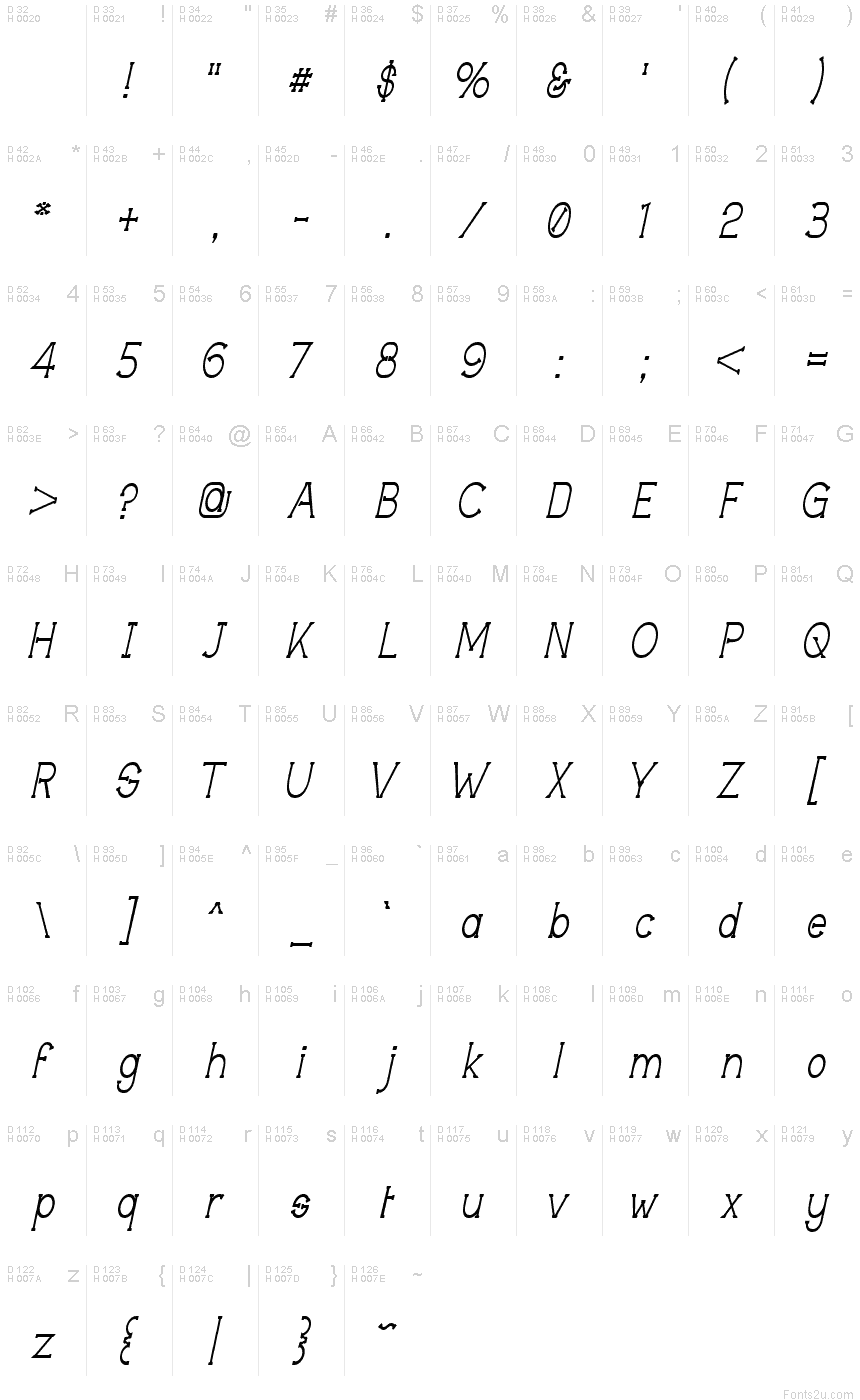
Technically Insane NarrowItalic
Technically Insane Narrow Italic od GemFonts98 to darmowy, techniczny krój pisma typu display, wyróżniający się ostrym, dynamicznym pochyleniem i smukłą sylwetką. Litery łączą w sobie płynne krzywizny z ostrymi, niemal przypominającymi ostrza załamaniami, dzięki czemu całość sprawia wrażenie futurystycznej, ale z lekkim pazurem, zamiast chłodnego dystansu.
Świetnie sprawdzi się w logo gier, plakatach sci-fi, ulotkach klubowych, planszach tytułowych i krótkich nagłówkach, gdzie to ukośne cięcie gra główną rolę. Jako darmowy font, idealnie nada się też do grafik w mediach społecznościowych czy wyrazistych monogramów, szczególnie gdy szukasz nowoczesnego, szybkiego i nieco drapieżnego wyglądu.